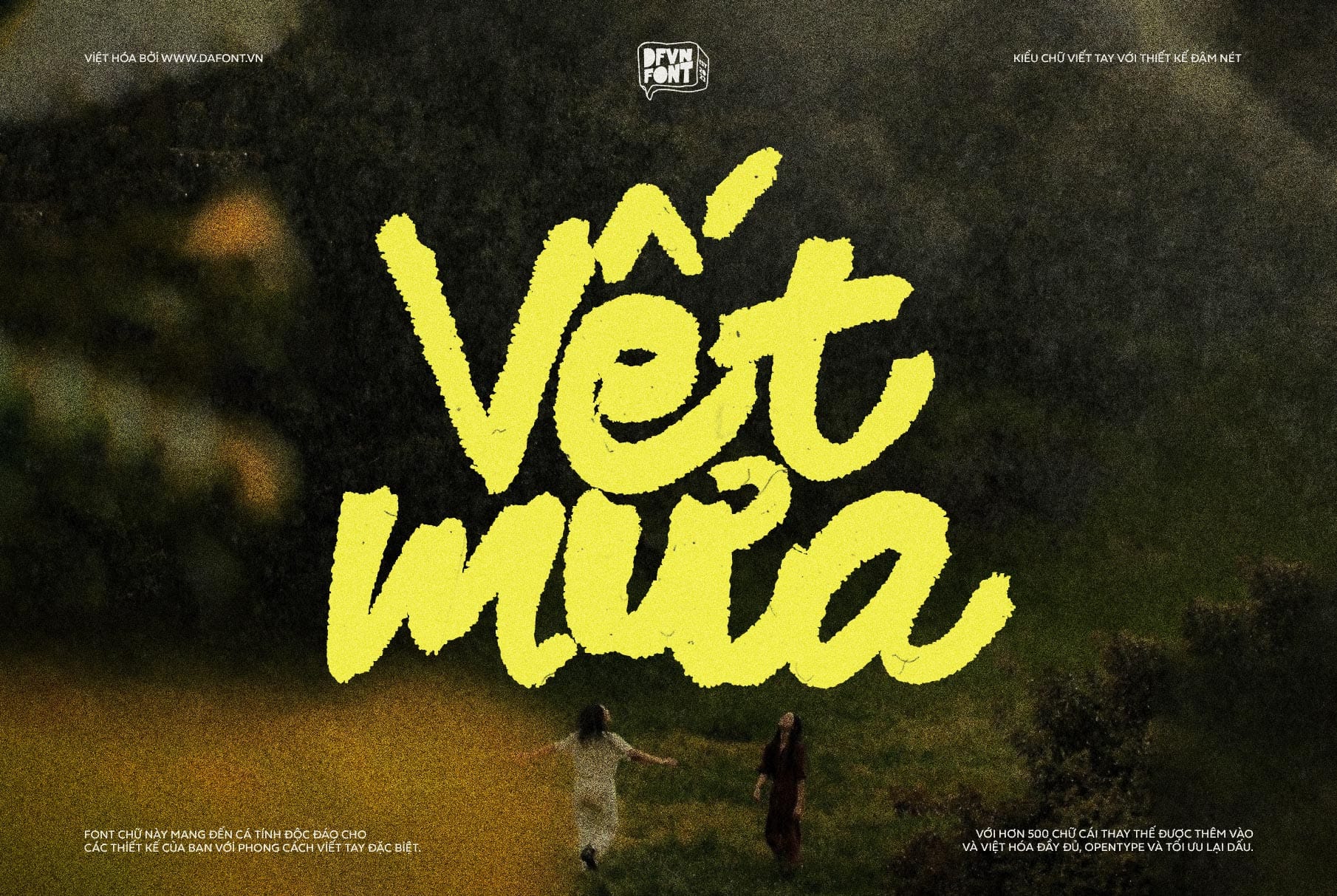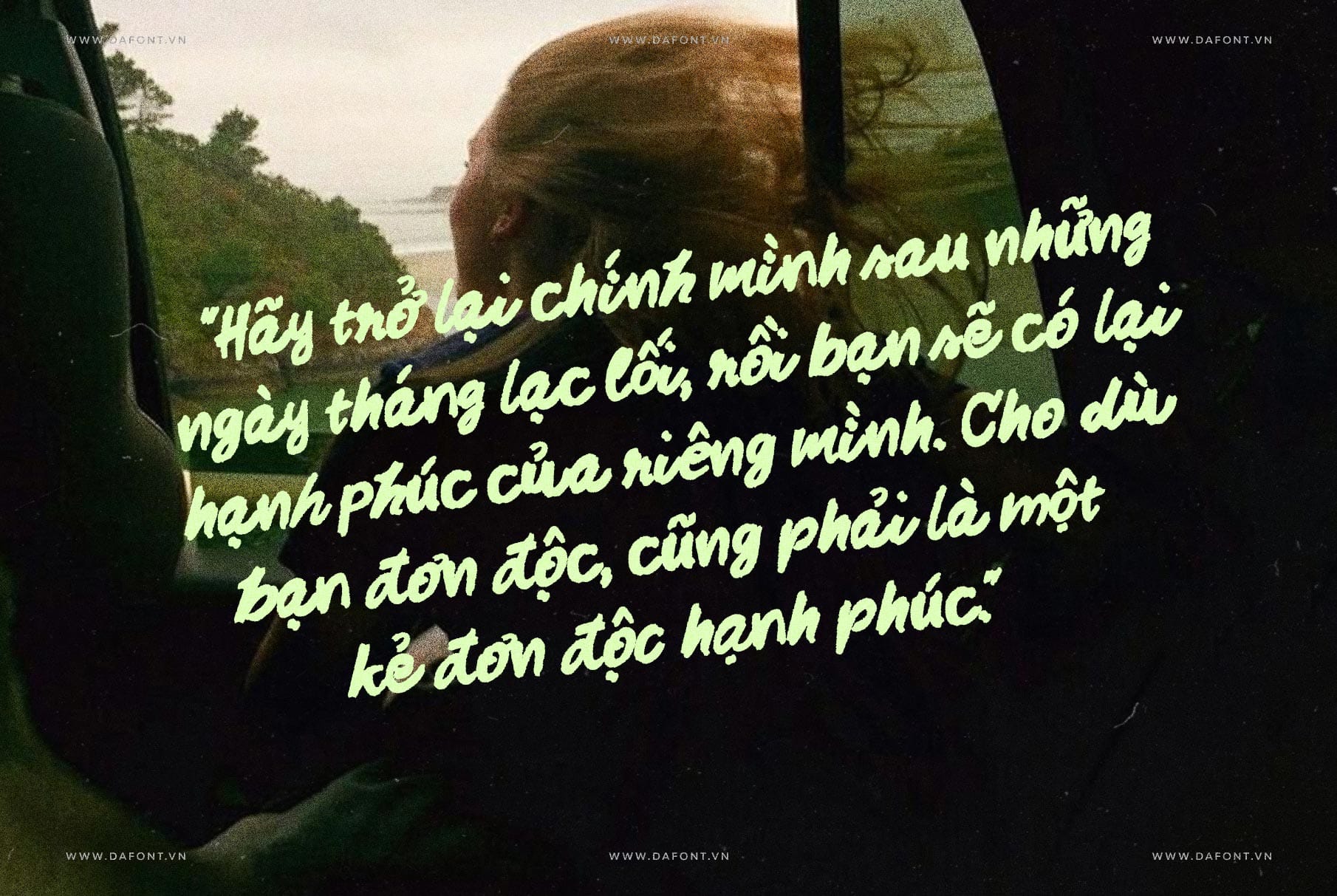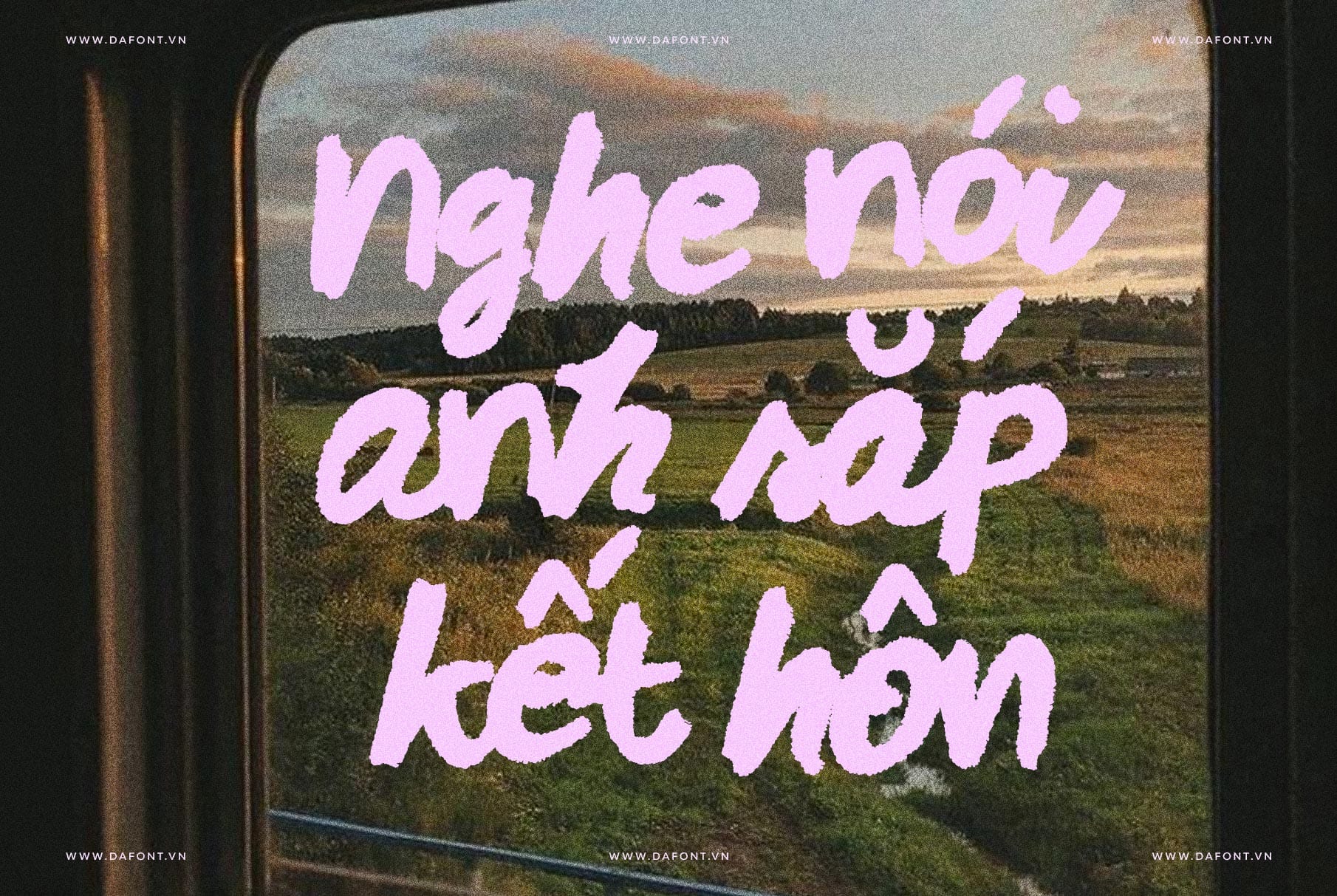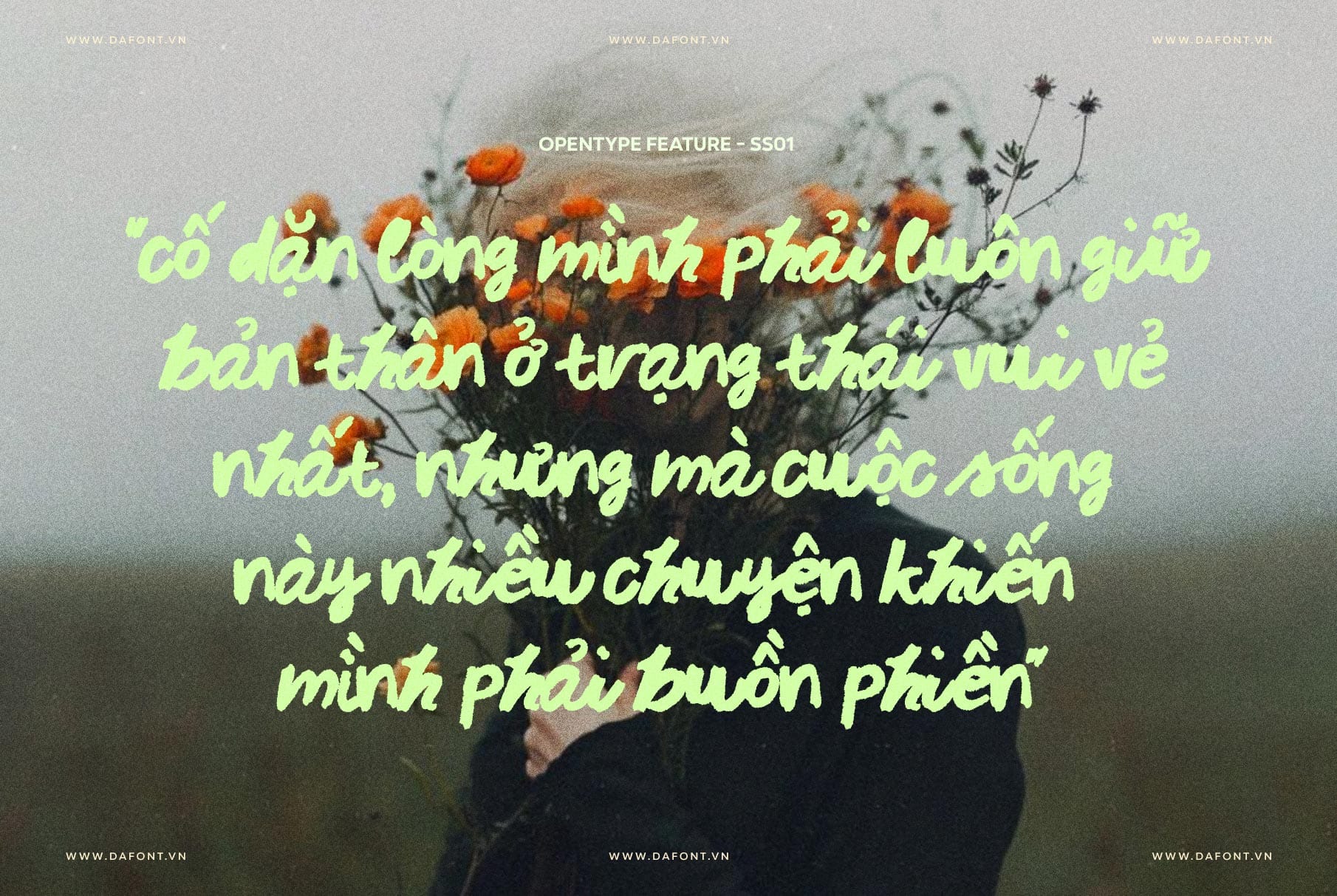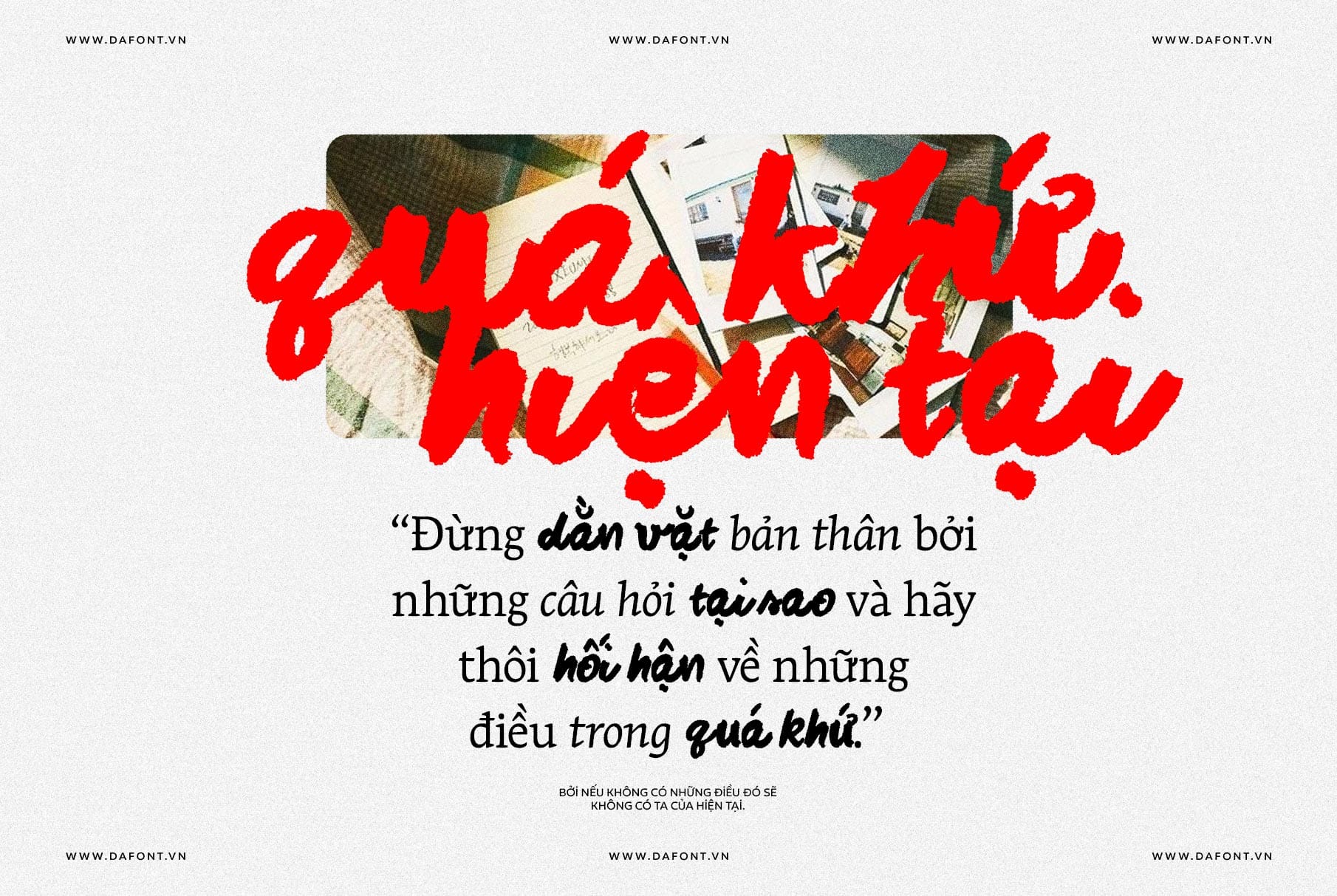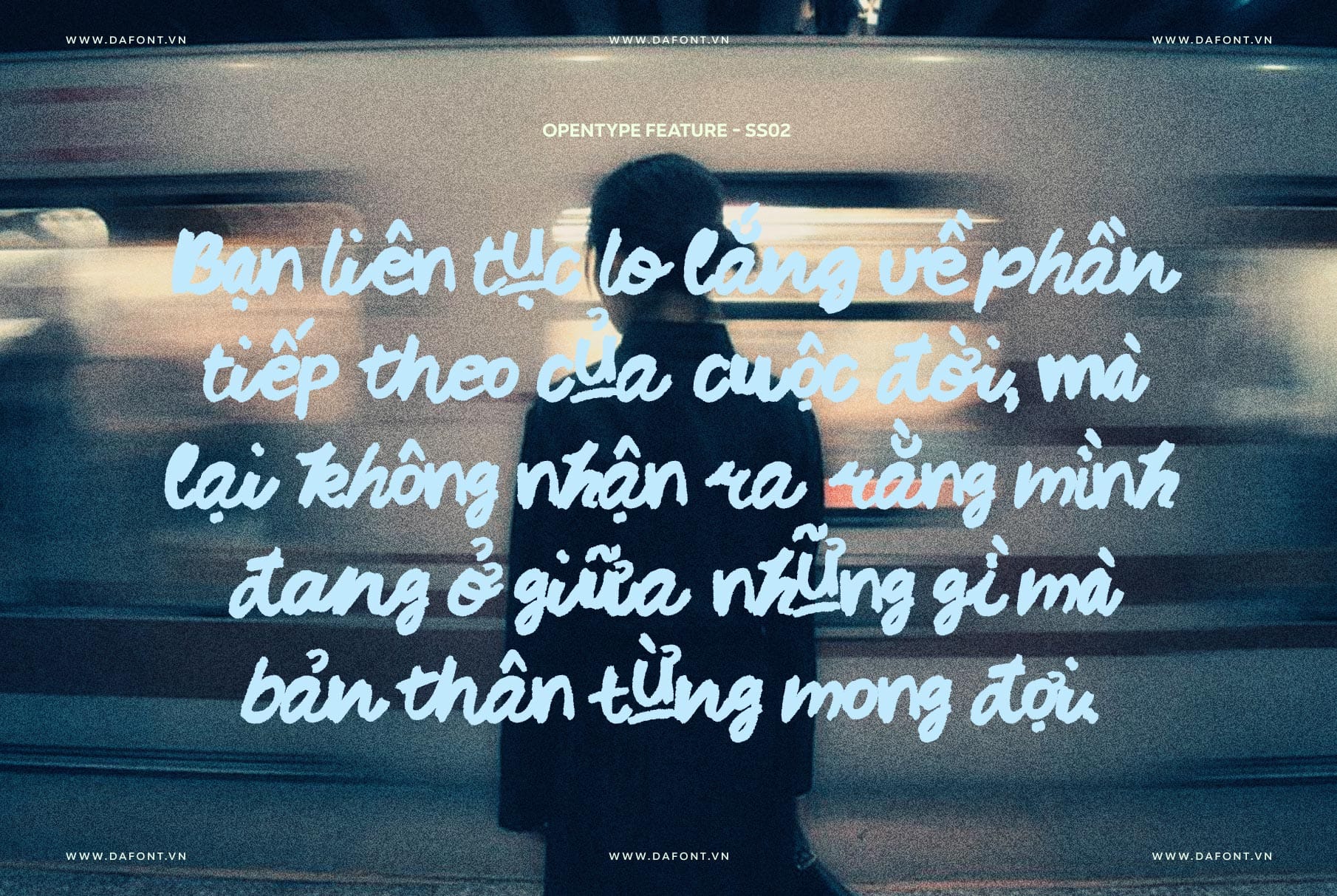
Bạn đang tìm kiếm một font viết tay Việt hóa độc đáo, hiện đại và đậm chất cá tính để nâng tầm dự án thiết kế của mình? DFVN Midnight Chianti chính là lựa chọn hoàn hảo! Với sự kết hợp giữa phong cách viết tay chân thực và tính ứng dụng đa dạng, font chữ này không chỉ làm nổi bật thiết kế của bạn mà còn giúp thương hiệu ghi dấu ấn mạnh mẽ.
Điểm nổi bật DFVN Midnight Chianti
Midnight Chianti là một font viết tay độc đáo, được thiết kế với sự chăm chút tỉ mỉ để mang lại cảm giác chân thực và hiện đại. font chữ này nổi bật với:
- Sáng tạo không giới hạn: Ba 3 chữ riêng biệt giúp bạn dễ dàng thay đổi phong cách, tăng tính linh hoạt cho mọi dự án – từ thiết kế logo, thiệp mời, bao bì đến ấn phẩm mạng xã hội..
- Hơn 50 chữ ghép (ligatures): Với hơn 50 ligatures tinh tế, font này tạo ra cảm giác viết tay liền mạch, chân thực như được viết bằng tay thật.
- Vẻ đẹp thủ công: Mỗi nét chữ trong Midnight Chianti đều được vẽ tay một cách tỉ mỉ, mang lại cảm giác chân thật, tự nhiên nhưng vẫn đảm bảo tính thẩm mỹ cao.
- Hơn 500 ký tự thay thế Việt hóa: Bổ sung và Việt hóa hơn 500 ký tự thay thế giúp linh hoạt hơn trong từng thiết kế.
DFVN Midnight Chianti – Phù hợp nhiều dự án thiết kế
Midnight Chianti font mang đến sự linh hoạt tuyệt vời cho mọi dự án thiết kế. Với phong cách viết tay đậm chất thủ công, font chữ này dễ dàng tạo điểm nhấn trong các thiết kế logo thương hiệu, giúp logo trở nên gần gũi, cá tính nhưng vẫn chuyên nghiệp. Trong bao bì sản phẩm, Midnight Chianti tạo cảm giác “handmade” tinh tế, đặc biệt phù hợp với các dòng sản phẩm thủ công, mỹ phẩm thiên nhiên, đồ uống thủ công…
Ngoài ra, khi sử dụng cho bài đăng mạng xã hội, font giúp thu hút ánh nhìn và thể hiện rõ “chất riêng” của thương hiệu, khiến nội dung trở nên sinh động và dễ tiếp cận hơn.
DFVN Midnight Chianti – Font viết tay Việt hóa không thể bỏ qua
Dù bạn là nhà thiết kế chuyên nghiệp hay chỉ đơn giản muốn làm đẹp cho dự án cá nhân, Midnight Chianti chính là “vũ khí bí mật” để truyền tải cảm xúc, cá tính và sự khác biệt. Hãy để từng nét chữ nói lên câu chuyện thương hiệu của bạn – bắt đầu với Midnight Chianti ngay hôm nay!